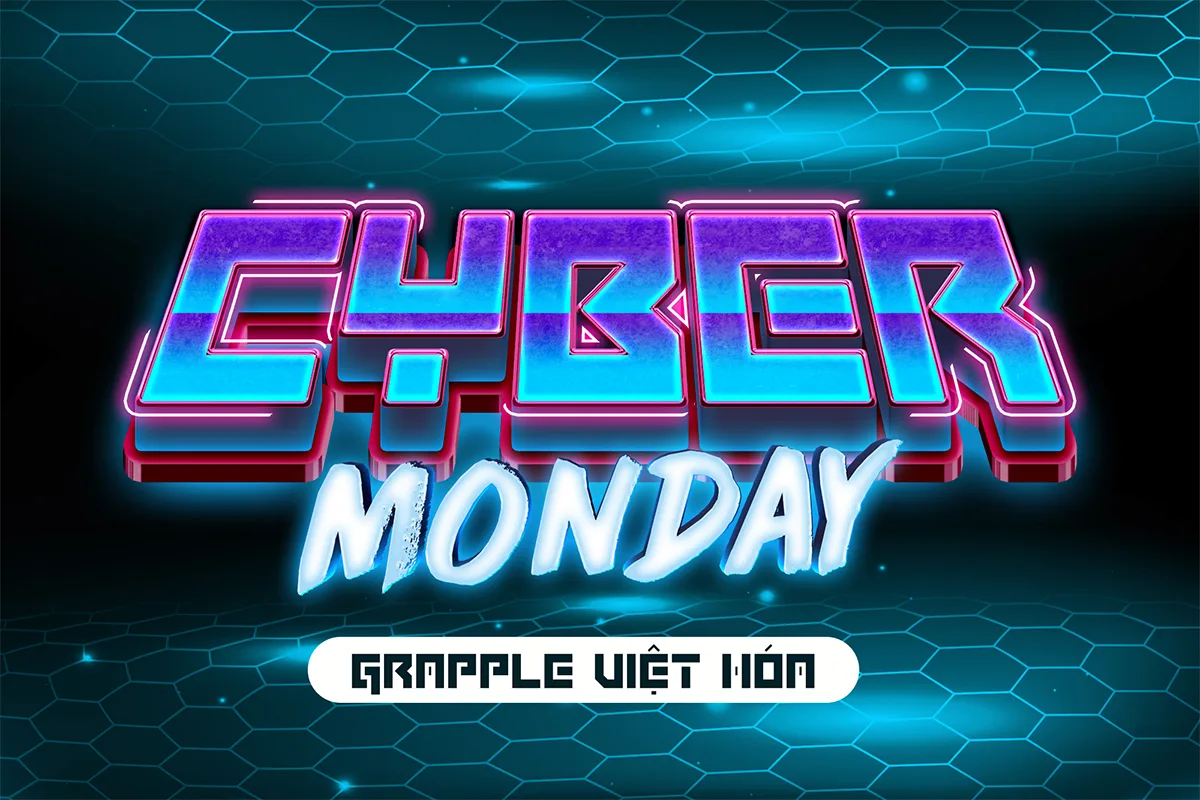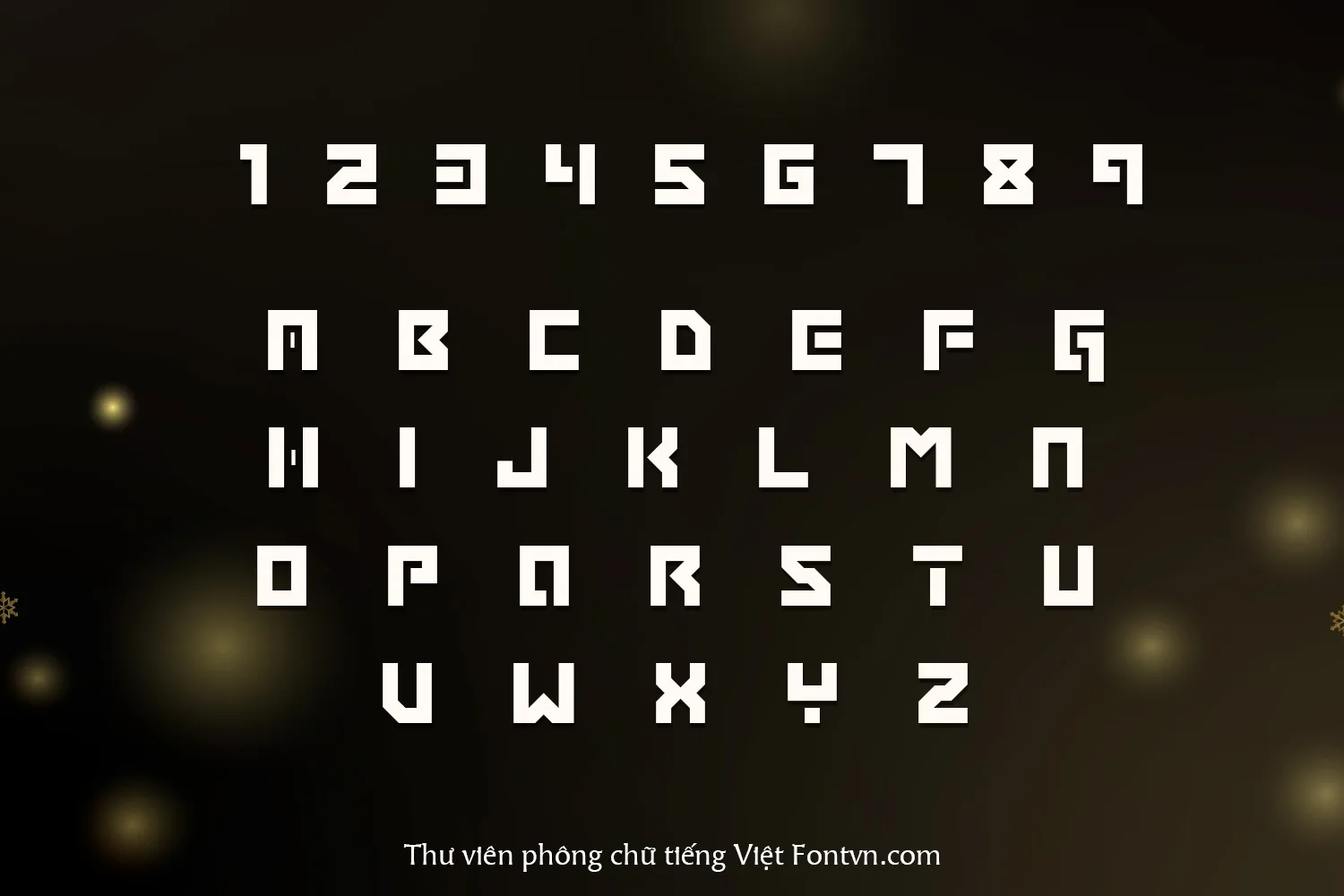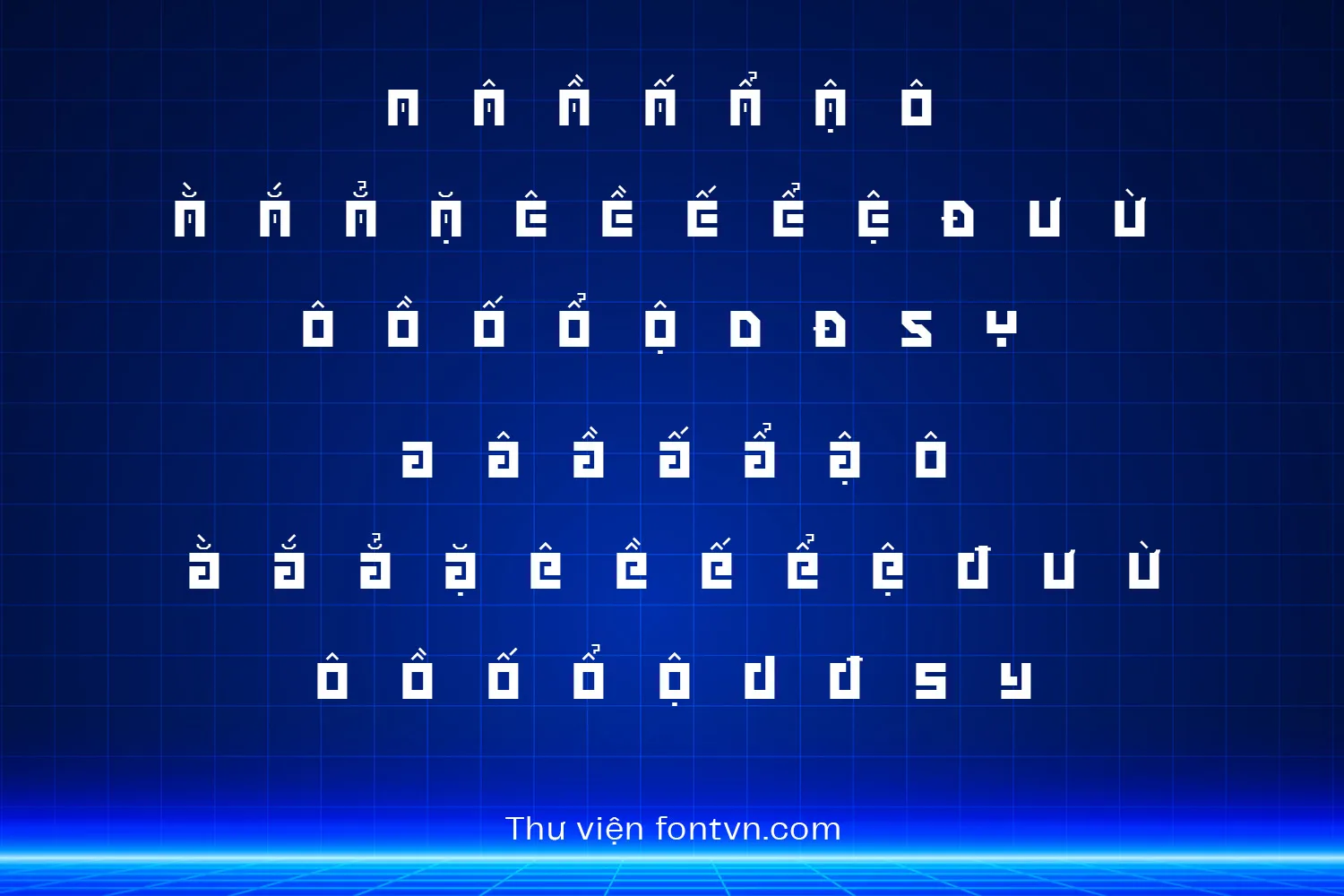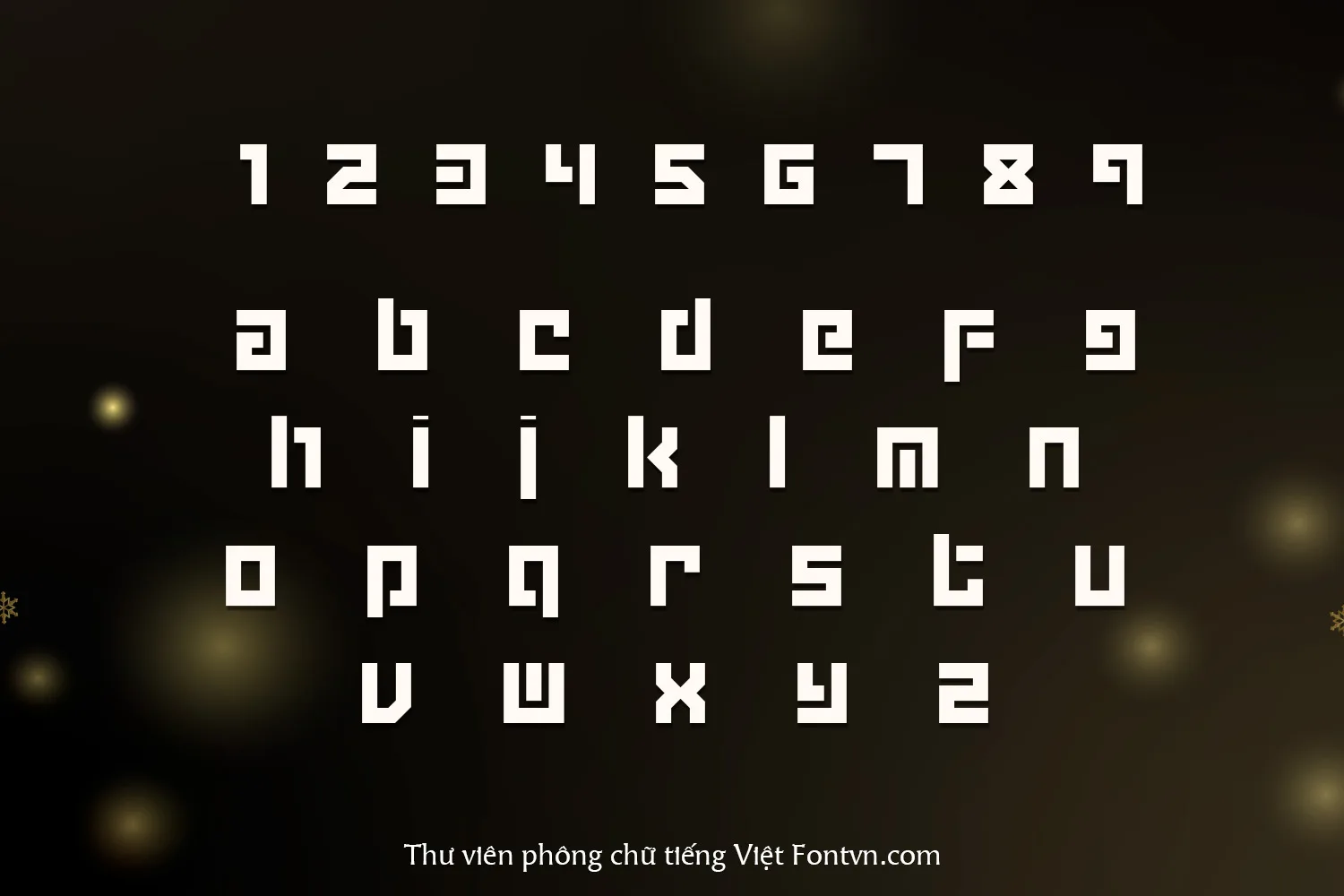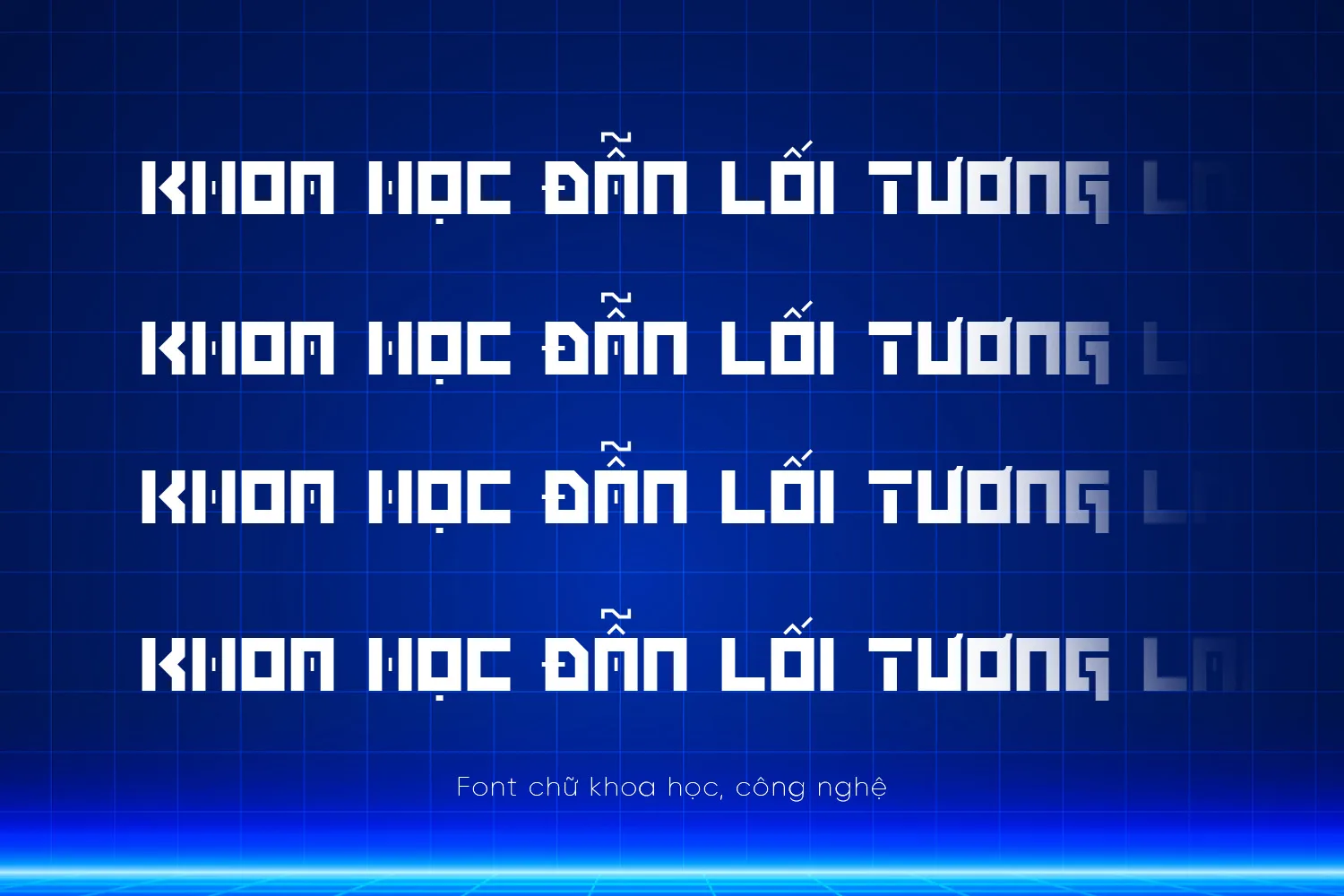
DVN Grapple Việt hóa – Font chữ công nghệ khoa học
DVN Grapple là phiên bản Việt hóa của font Grapple BRK, mang phong cách techno hiện đại, góc cạnh và đậm chất công nghiệp. Font sở hữu những nét chữ vuông vức, chắc chắn với các đường cắt táo bạo, tạo cảm giác như được đúc từ kim loại hoặc thiết kế theo dạng stencil công nghệ. Với khả năng hỗ trợ tiếng Việt đầy đủ, DVN Grapple là lựa chọn lý tưởng cho các dự án thiết kế poster, game, giao diện app, hoặc những sản phẩm cần truyền tải sự mạnh mẽ, lạnh lùng và mang hơi hướng tương lai. Font phù hợp với các tiêu đề lớn, nhấn mạnh yếu tố hình khối, không gian và sự chính xác. DVN Grapple không chỉ gây ấn tượng mạnh ở cái nhìn đầu tiên mà còn mang đến một trải nghiệm thị giác độc đáo cho bất kỳ dự án sáng tạo nào.
Nếu bạn cần biến hóa thiết kế thành ngôn ngữ công nghệ, DVN Grapple chính là lựa chọn đáng cân nhắc.